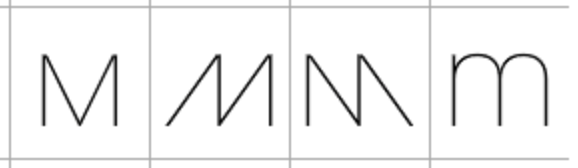
ich suche die Schriftart des angehängten Bildes. Leider ist dies das einzige Bild, dass ich
vorzuweisen habe. Das Bild stammt von dem Berliner Modelabel "Muschi Kreuzberg" und ist von 2013. Ich benötige die Schriftart für ein Geburtstagsgeschenk und würde mich sehr über eure Hilfe freuen!
Automatische Dienste und das durchsuchen eurer Datenbank haben mich bislang noch nicht zum Erfolg gebracht, also vertraue ich nun auf die Profis ;)
Da ich genau dieses Schriftzug benötige sind auch M und A von Bedeutung, irgendwelche Ideen woher diese stammen könnten?
Die Buchstaben sind als Alternativglyphen in der Schrift enthalten. Beim A bin ich mir nicht sicher, ob es regulär ohne den Querstrich dabei ist, den müsste man bei Bedarf selber herausnehmen.
Screenshots aus der Glyphentabelle:
Die sind als Alternativbuchstaben enthalten. Allerdings mit dem Querstrich beim A, den müsstest du entfernen.
Auf Deviant-Art habe ich schon mehrere von der Avant Garde inspirierte Fonts gesehen z.B. Demon Breeze, Devil Breeze, Wet Dreamz, Illegal Curves (Einsicht? :twisted:) , Avante Go, Avante Return, Avant Garde Guetta usw. Genau die gesuchte Schriftart habe ich dort aber auch nicht gefunden.